So wählen Sie die richtige Schrift für Ihr Projekt.
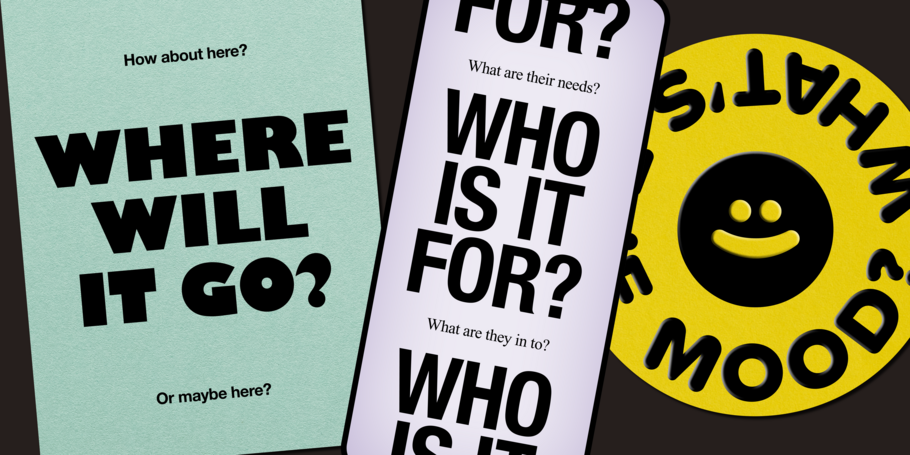
„Wie finde ich die richtige Schrift?“
„Woran sollte ich denken, wenn ich Fonts für ein Projekt auswähle?“
„Wie wählen Sie bestimmte Schriften für bestimmte Projekte aus?“
„Ich habe ein Projekt, das eine neue Perspektive benötigt. Wie kann ich Schrift einsetzen, um es herauszuheben?“
Das sind Fragen, die mir als Designer mit einer besonderen Liebe zur Typografie in meiner 20-jährigen Laufbahn immer wieder gestellt wurden. Manchmal war es schwierig, die Antwort zu formulieren. Deshalb habe ich mich vor ein paar Tagen hingesetzt und meinen persönlichen und beruflichen Prozess bei der Auswahl der richtigen Schrift für einen Job niedergeschrieben.
Es ist keine Hexerei und erfordert nur etwas Nachdenken.
Wenn Sie bis hierhin gelesen haben, gehe ich davon aus, dass Sie wissen, wie wichtig es ist, die richtige Schrift für ein Projekt zu wählen. Warum sonst würden Sie im Netz nach Anregungen für die Wahl der richtigen Fonts für ein Projekt suchen? ;-) Auf der Basis dieser Annahme möchte ich im Folgenden kurz erläutern, wie ich meine Fonts auswähle.
Um es gleich vorwegzunehmen: Ich habe weder große Geheimnisse noch sensationelle Enthüllungen aus meiner 20-jährigen Karriere als Designer und Typograf auf den Tisch zu legen. Vielleicht ist es einfach nur hilfreich, etwas über den Prozess der Eingrenzung von Optionen zu erzählen. Wenn man einmal anfängt, über die Wahl der Schrift nachzudenken und sich bewusst Zeit dafür nimmt, wird das Resultat immer besser.
Was sind Ihre technischen Anforderungen?
Wie bei allen Designprojekten beginne ich immer damit, die Grenzen zu bestimmen und Fragen zu stellen. Gibt es bestimmte Anforderungen für den Einsatz der Schrift? Benötigen wir die Schrift für riesige Plakatwände oder für das Kleingedruckte in einem Flyser … oder für beides? Entwerfe ich etwas, was überwiegend am Bildschirm oder auf Papier gelesen werden soll? Handelt es sich bei dem neuen Projekt um die Benutzeroberfläche einer mobilen App, um einen langen, redaktionellen Beitrag oder ein gedrucktes Buch? Benötigen wir jetzt oder in Zukunft spezielle Sprachunterstützung?
Meiner Erfahrung nach gibt es bei Branding- und Corporate-Design-Projekten eine Unmenge von Anwendungen: vom Großflächenplakat über das Packaging bis zu Flyern und der Geschäftsausstattung. In solchen Fällen schlage ich vor, eine Schriftfamilie mit mehreren optischen Größen zu wählen, die Textgrößen wie Headline (größer 18 Punkt), Fließtext (zwischen 8 und 12 Punkt) und Mikrotext (kleiner 8 Punkt) abdecken. Bei einer solchen Schrift sind die Optische-Größe-Varianten auf der Glyphen-Ebene bis in die feinsten Details so gestaltet, dass die Texte in allen Größen einheitlich aussehen und eine maximale Lesbarkeit garantieren. Je nach Schriftdesigner gibt es unterschiedliche Bezeichnungen für die optischen Größen, aber in der Regel gibt es eine „Display“-, eine „Text“- und eine „Micro“-Subfamilie, die man in die Textilgrößen Large, Medium und Small übersetzen und entsprechend einsetzen kann.
Ich bin ein großer Fan von Monospaced-Fonts (nichtproportionale oder dicktengleiche Schriften) … für kleine Info-Texte oder für die Darstellung von Daten. Monospaced-Fonts sind Schriften, bei denen jedes Zeichen die gleiche Breite hat – also der typische Schreibmaschinen- oder Nadeldrucker-Look. Sie vermitteln den Leserinnen und Lesern das Gefühl einer präzisen, aktuellen, technischen Information. Ich verwende sie gerne für Bildunterschriften, Infografiken und immer dann, wenn ich Daten oder Fakten auf überzeugende Weise darstellen muss.
Denken Sie auch an Ihre Zielgruppe und daran, wie international Ihr Produkt ist (oder werden könnte). Wenn Ihre Kunden oder Auftraggeber die Schrift in mehreren Sprachen lesen oder verwenden sollen, müssen Sie sicherstellen, dass die von Ihnen gewählten Fonts die relevanten Sprachen unterstützen, also Akzentbuchstaben, Fremdsprachen-Zeichensätze und die Schreibrichtung enthalten. Ich spreche hier aus Erfahrung: Sie wollen nicht mitten in einem Projekt feststellen, dass die ursprünglich gewählte Schrift keine Umlaute, keine osteuropäischen Buchstaben oder keine kyrillischen Zeichen enthält, und dann wieder nach einer neuen Schrift suchen. Das Arbeitsleben ist zu kurz, für solche Zeitverschwendungen, oder?
Wer ist Ihr Publikum?
Wie bei mit der Sprachunterstützung frage ich mich auch bezüglich des Designe, wer meine Entwürfe oder Produkte nutzen wird: Ist die Zielgruppe jung oder alt? Ist sie technisch versiert oder fängt sie gerade erst an zu lernen? Benutzen die Empfänger die neuesten Geräte oder hinken sie der Technologie etwas hinterher? Kommen die Nutzer aus einem bestimmten geografischen Gebiet oder sind sie weltweit unterwegs?
Wie Sie sich denken können, hat das Design für eine wissenschaftliche Zeitschrift eine andere visuelle Ästhetik als Aufkleber, die Sie über TikTok oder Instagram Reels verbreiten möchten. Wenn Sie auf der Suche nach einer Schrift sind, die aktuell und im Trend liegt, sollten Sie sich den Monotype Schrift Trends Report 2023 ansehen, um sich über weltweite Trends und visuelle Stile zu informieren. Wenn Sie einen eher „klassischen“ Ansatz suchen, sollten Sie eine Serifenschrift wie Cotford von Tom Foley und dem Monotype Studio, Macklin von Malou Verlomme und dem Monotype Studio oder Paperback von John Downer und House Industries in Betracht ziehen.
Falls Sie einen geltenden Markenleitfaden haben, müssen Sie sich natürlich an diese Richtlinien halten. Aber verzweifeln Sie nicht: Es gibt stets Raum zum Experimentieren! Im Laufe meiner Karriere war ich immer wieder überrascht, wie sehr ich die Markenrichtlinien durch geschickte Entscheidungen oder die Verwendung vorhandener Schriften auf unerwartete Weise neu interpretieren konnte.
Ein weiterer Tipp: Um sicherzugehen, dass ich nicht einfach kopiere, was alle anderen machen, erstelle ich oft ein Moodboard, das zeigt, was andere in einem ähnlichen Bereich gemacht haben. Entwickeln Sie eine neue Marke für ein Technologieunternehmen? Ich würde Ihnen raten, nicht einfach eine andere geometrische serifenlose Schrift zu verwenden! Wenn alle Ihre Konkurrenten eine bestimmte Schrift verwenden, sollten Sie das Gegenteil ausprobieren, um Ihr Produkt von den anderen abzuheben. Sind in letzter Zeit alle auf den Zug „verrückte, 70er-Jahre, groovige, Patagonia-ähnliche Schrift“ aufgesprungen? Ich schlage vor: Wählen Sie stattdessen etwas Ausdrucksstarkes, das Ihr Design von den aktuellen Trends abhebt.
Wählen Sie den Kontrast.
Bei der Suche nach der richtigen Schrift wähle ich am liebsten Fonts, die einander kontrastieren. Die Wahl von Helvetica und Futura (zwei serifenlose Schriften) ist meiner Ansicht nach kein Kontrast, auch wenn sie – stilistisch betrachtet – unterschiedlich sind, Helvetica als eine Neo-Grotesk und Futura als geometrische Sans.
Meine Idee für eine kontrastreiche Schrift-Paarung ist, zwei Schriften von ein- und derselben Person zu wählen, die stilistisch weit auseinander liegen, zum Beispiel Questa Serif und Scala Sans von Martin Majoor, oder Serifa und Univers von Adrian Frutiger. Designer haben ihre eigene Herangehensweise an das Schriftdesign, und das kann man oft zwischen Entwürfen mit sehr unterschiedlichem Stil erkennen. Selbst wenn zwei Schriften sehr unterschiedlichen Genres angehören, habe ich die Erfahrung gemacht, dass zwischen den Entwürfen eine Harmonie herrscht, weil die Person, die sie entworfen hat, dieselbe ist. Das gilt natürlich nicht für alle Designer oder Situationen, aber es hilft mir oft, ähnlich aussehende Schriften einzugrenzen.
Die Wahl zwischen einer Serifen- und einer Groteskschrift kann sich endlos hinziehen, weil das Angebot riesig ist. Mein Tipp dazu: eine kräftige Serifenschrift mit viel Kontrast in der Strichstärke zu wählen (also dünne oder fette Serifen mit kontrastierenden Stämmen). Wenn Sie sich für eine Serif entschieden haben, suchen Sie sich eine guta ausgebaute Sans, die Ihnen gefällt, und greifen Sie zu einem leichteren Schnitt als Normal. Die geringere Strichstärke der serifenlosen Schrift kann bei größeren Anzeigeformaten zum Blickfang werden, wegen der ungewöhnlichen Kombination, die der Typografie einen Hauch von Frische verleiht.
Bauen Sie eine Familie auf.
Es gibt viele Anleitungen für das Finden eines harmonischen Schriftpaars. Ich bevorzuge allerdings ein Schrifttrio, um maximale Flexibilität beim Mischen und Kombinieren zu erreichen. Die Wahl eines Trios aus Display-, Text- und Mikrotext-Fonts gibt Ihnen viel Spielraum, um sowohl eine solide typografische Grundlage zu schaffen als auch Spielraum zu haben.
Als Beispiel für die Auswahl von Schriften desselben Designers (oder in diesem Fall von zwei Designern) würde ich etwa dieses Trio von den talentierten Designern von Process Type Foundry wählen: Colfax für Bildschirmtexte, Elena für Fließtexte und längere Texte und die Monospace-Schrift Recipient für Bildunterschriften, Kleingedrucktes und Datenvisualisierung. Wenn Sie das Gefühl haben, dass eine dicktengleiche Schrift nicht in Ihr Konzept passt, empfehle ich eine Schrift wie Operator, die das visuelle Styling einer Monospace hat, aber immer noch proportional ist und etwas weniger Aufmerksamkeit auf sich lenkt.
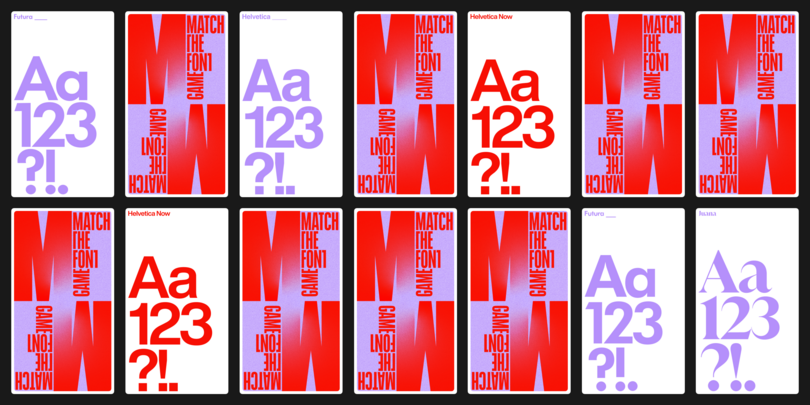
Übung bringt sich weiter.
Ich möchte nicht verschweigen, dass die Auswahl der richtigen Schriften für ein Projekt Zeit, Übung und Erfahrung erfordert. Wenn Sie nicht auf Anhieb ein gutes Font-Trio finden, lassen Sie sich nicht entmutigen! Ich habe immer noch Schwierigkeiten mit der Kombination und Auswahl von Schriften, und das seit fast 20 Jahren. Wie bei den meisten lohnenden Dingen im Leben ist es auch hier so: Je mehr man sich damit beschäftigt, desto besser wird die Wahrnehmung von Schrift, die Beurteilung von Kombinationen und die Auswahl.
Viel Glück und nicht aufgeben!